Una tipografía de chorizo
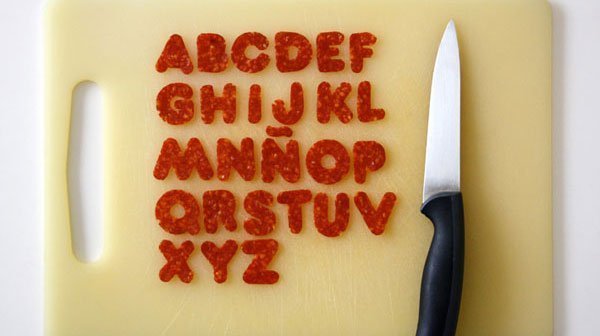
El bocadillo de chorizo es una institución en este país. La merienda (un estudio de diseño gráfico que tiene una galleta como logo, unas onzas de chocolate como icono de Facebook y una pizza de enlace a Twitter) ha decidido rendir homenaje a todos esos panes con chorizo que han caído durante miles de tardes para matar el hambre entre la comida y la cena.
El estudio especializado en dirección de arte lo ha hecho con una tipografía elaborada con chorizo de verdad. Del que viene del cerdo y del que pringa las manos. Rodajas de chorizo de Pamplona y, según dicen en su blog, «mucha paciencia».
la w se la han comido!
Se han hehco un bocata con la W